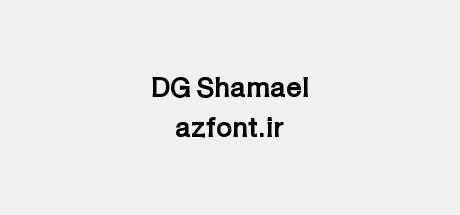
DG Shamael
فونت زیبای رایگان DG Shamael
قلم زیبای DG Shamael Bold از سری قلم های بسیار زیبا برای تایپوگرافی و لوگو تایپ می باشد.این قلم در وزن Bold و توسط https://twitter.com/HossamElNazawy طراحی و منتشر شده است.